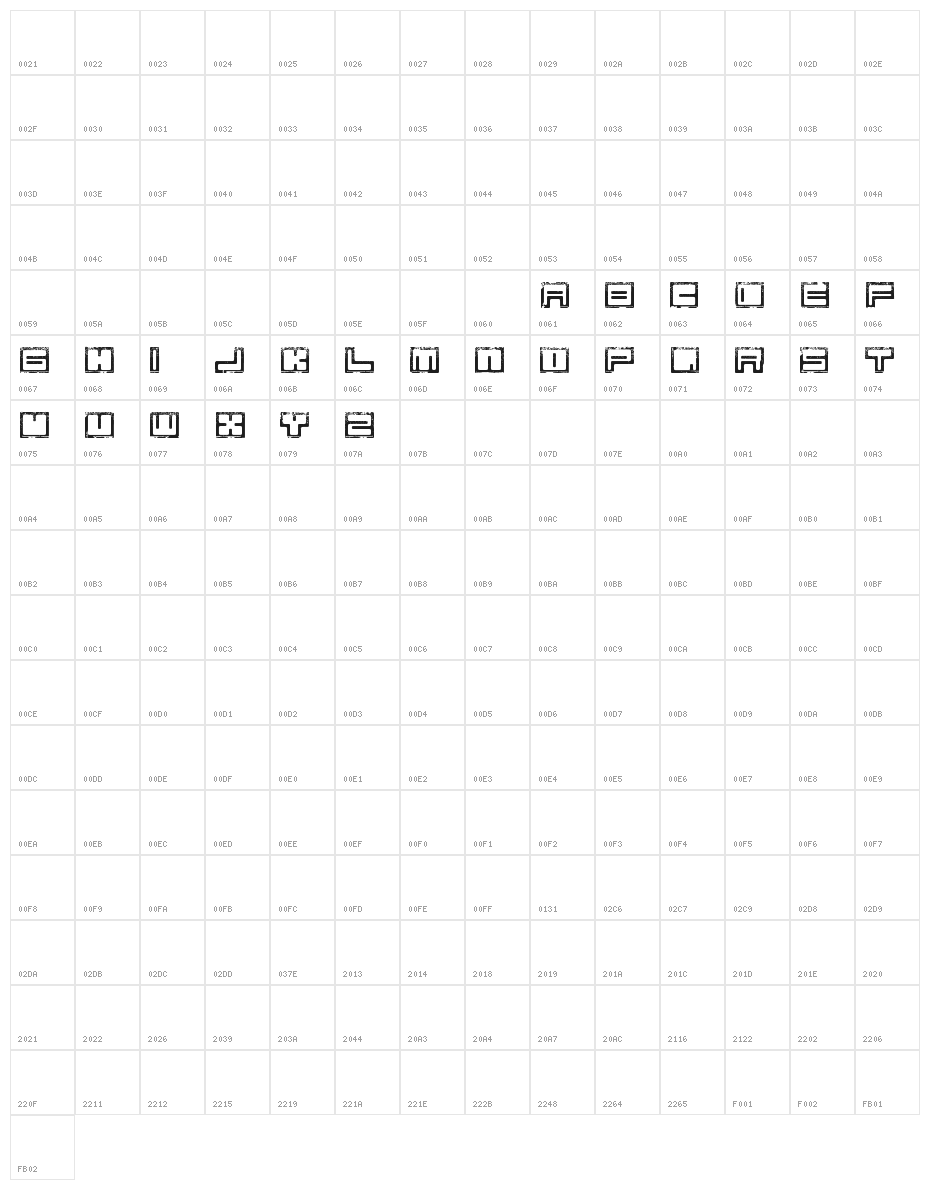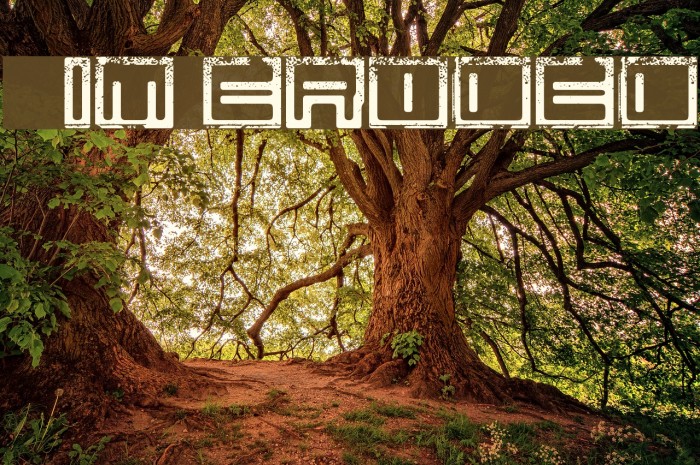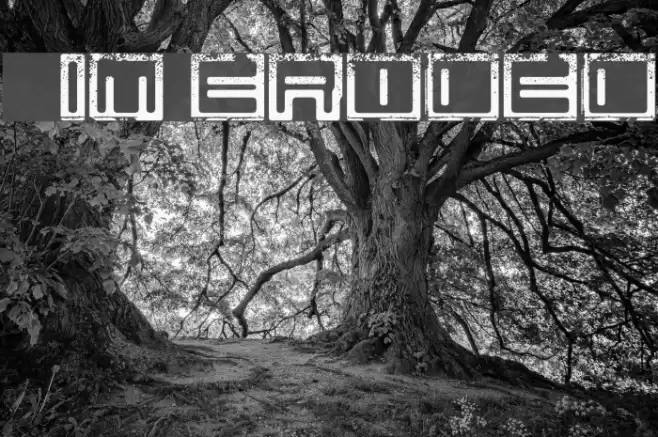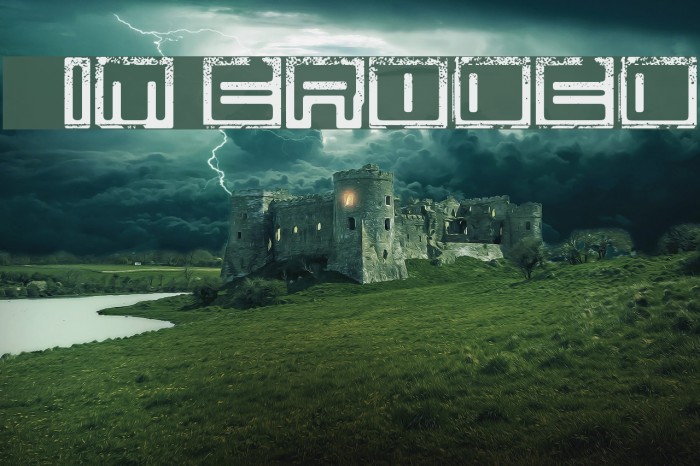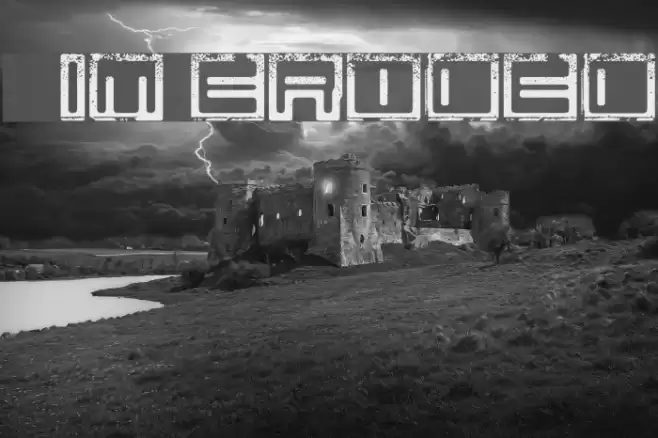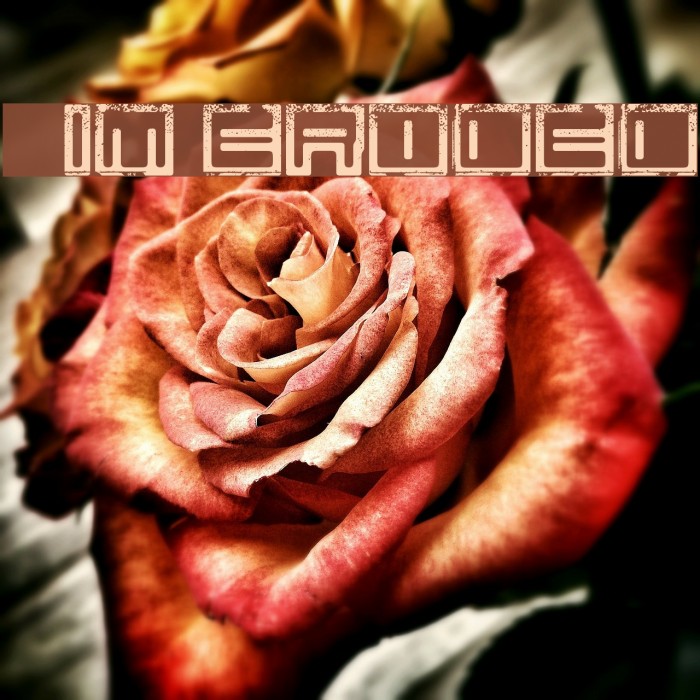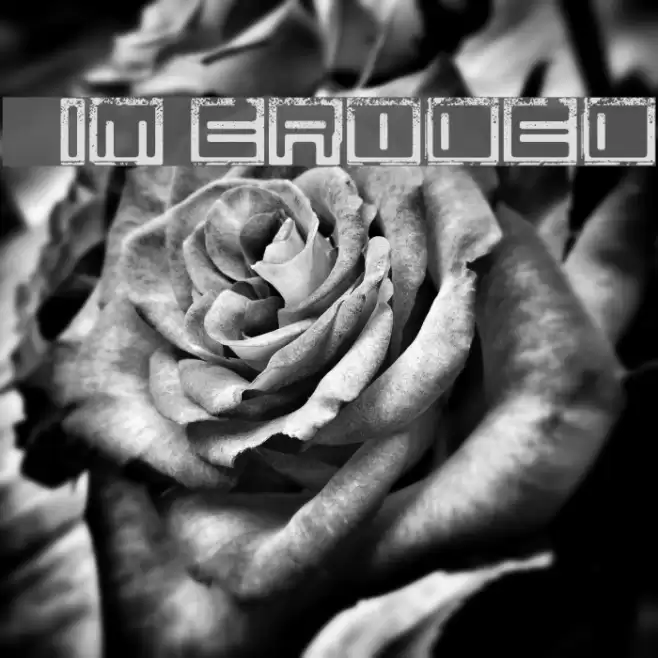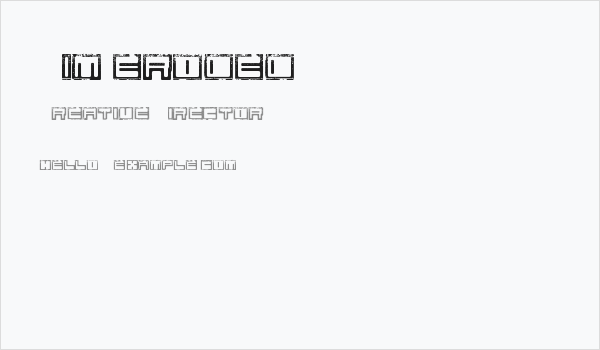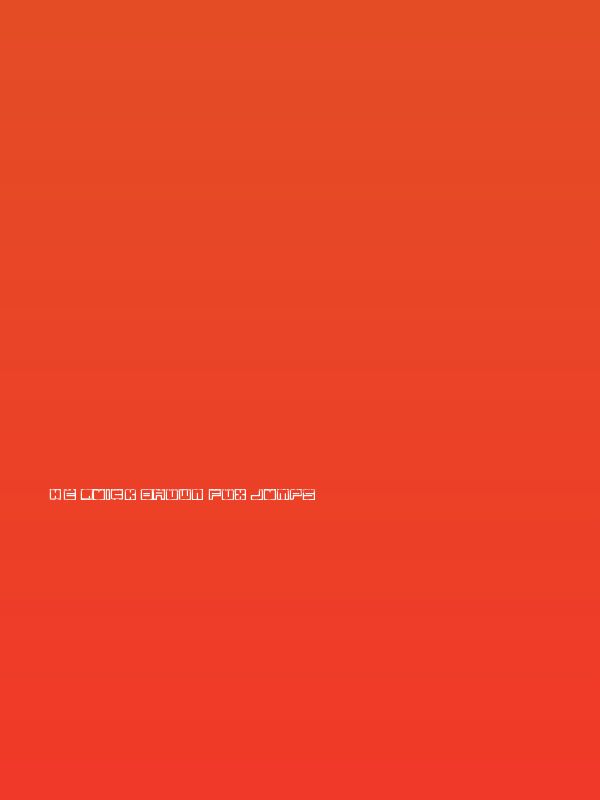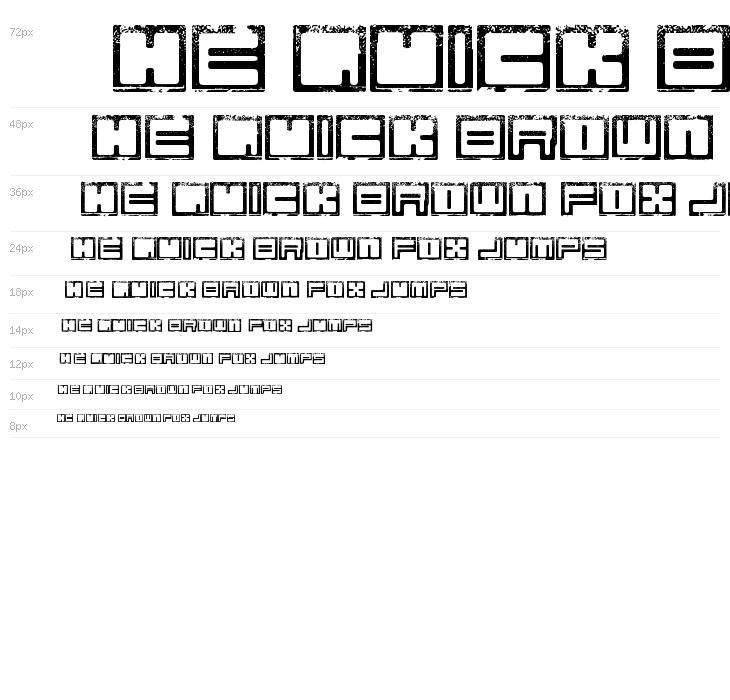
Bim eroded Font
✎ Distorted Eroded
| Progetti proposti | Ideal for posters, album covers, branding for outdoor or adventure products, and any design needing a vintage or grunge feel. |